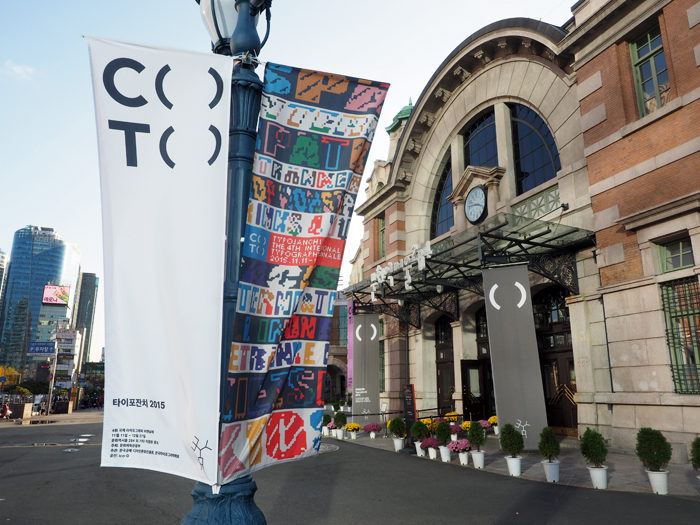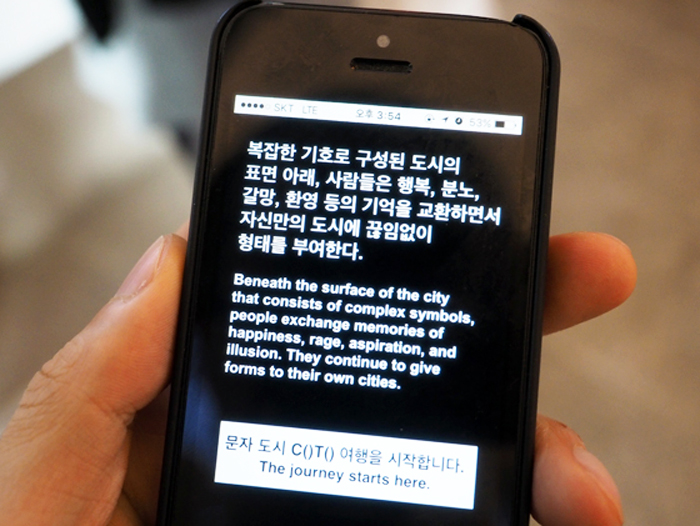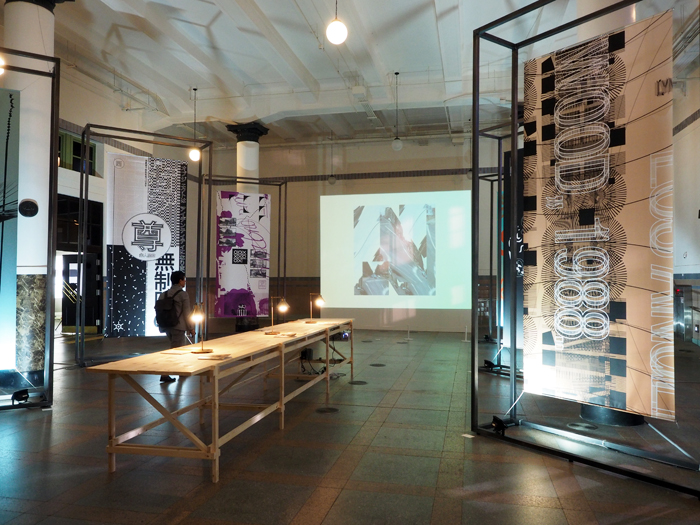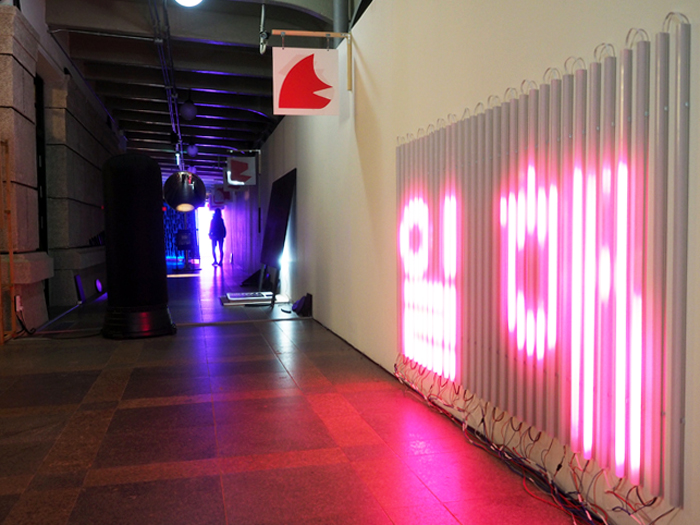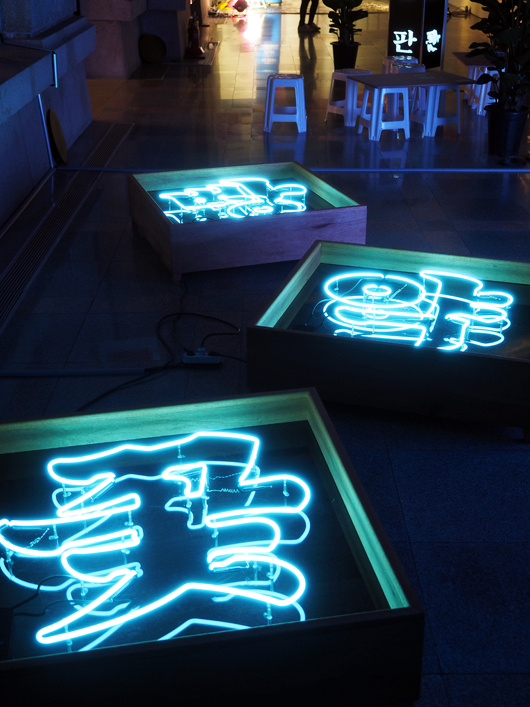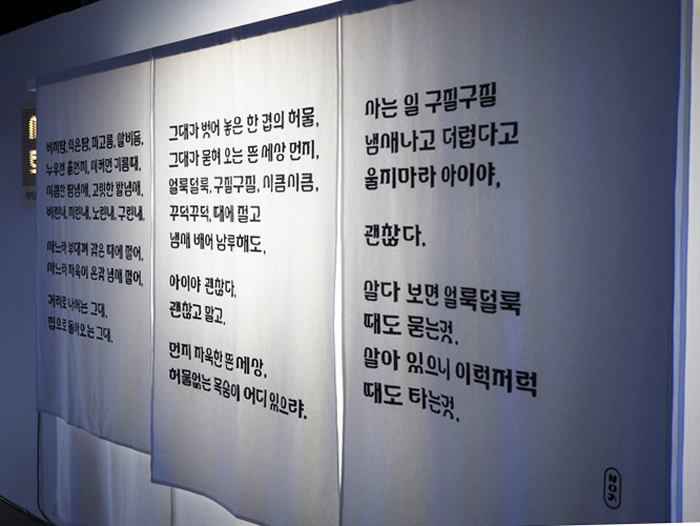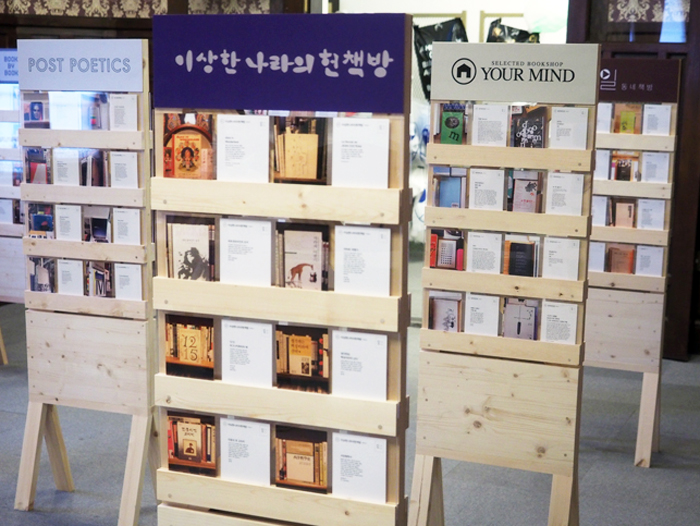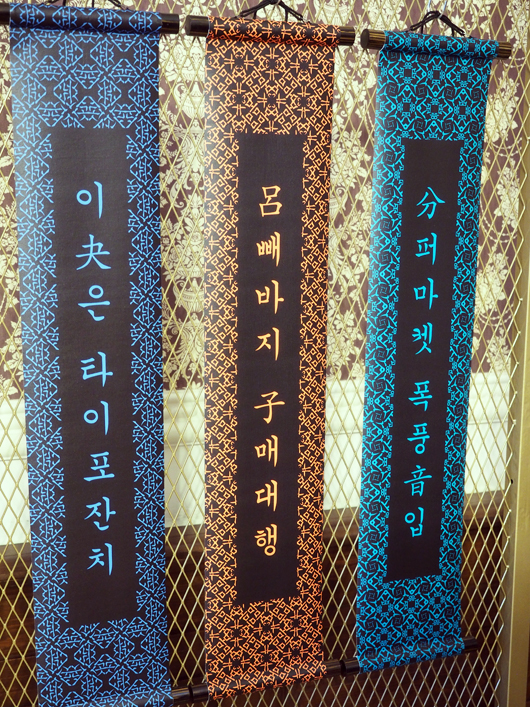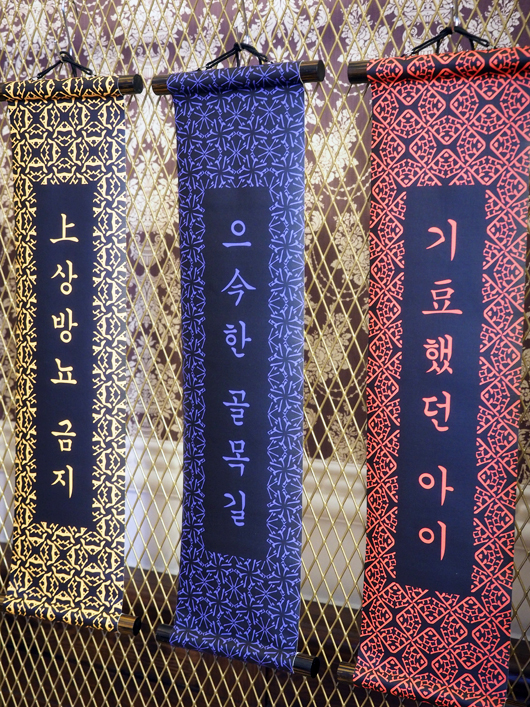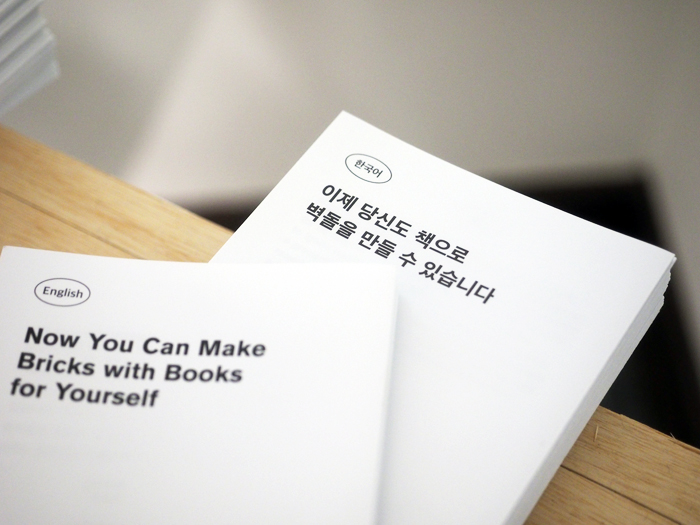
타이포잔치 2015 : 도시와 문자, 그 긴밀한 관계 속으로
올해로 4회를 맞은 ‘국제타이포그래피비엔날레(타이포잔치)’는 세계 22개국 91명의 작가가 참여해 준비한 세계 유일의 타이포그래피 비엔날레다. 이번 타이포잔치 2015의 주제는 ‘도시와 문자’다. ‘도시’라는 문명의 터전에서 문화의 가장 기본이 되는 문자가 어떻게 살아 숨쉬며 우리와 호흡하고 있는지를 다양한 작품들에서 만날 수 있다. 오는 12월 27일까지 문화역서울284에서 진행된다.
타이포잔치 2015 : 제4회 국제타이포그래피비엔날레
“일어나서부터 잠들기까지, 우리의 일상에서 문자가 없어진다면 어떻게 될까?”
매일 아침 습관적으로 쳐다보는 스마트폰 화면이 텅 비어있다면? 스마트폰 뿐만 아니라 컴퓨터에도, TV에도, 신문에도, 도로에도, 지하철에도 아무런 글자가 없다고 상상해보라. 우리의 일상은 급브레이크를 밟은 것처럼 큰 파열음을 내며 멈출 수 밖에 없을 것이다. 특히 대도시에 살고 있다면 더욱 그렇다. 이 거대하고 복잡한 도시가 아무 문제없이 자연스럽고 원활하게 유지되기 위해서는 문자라는 문명의 질서가 반드시 필요하다. 우리에게 문자는 산소와 같다. 인간의 문명과 문화에서는 문자란 언제나 존재해야 하는 것이다.
“타이포잔치가 도시를 주제로 삼은 것은, 아마도 사람의 삶이 가장 복잡하게 뒤섞인 곳이기 때문에 도시 구석구석에 스며 있는 문자들의 생태가 궁금해서였을 것이다.
‘C( )T( )’라는 타이포잔치의 로고에 포함된 ‘( )’는 다양한 해석과 참여를 의미하기도 하지만, 도시를 횡단하는 여러 단면을 끌어내어 담아내보려는 의도가 포함되어 있다.”
-민병걸, ‘결여의 도시’ 큐레이터
타이포잔치는 이런 사실을 극명하게 보여준다. 심지어 여기서 한발 더 나아가 문자와 타이포그래피를 우리 생활의 주역으로 끌어올린다. 언제나 조연에 불과하던 이들이 주인공이 되어 선사하는 풍경은 충분히 이색적인 경험이다. 이차원적인 평면에 납작하게 붙어있던 문자들이 도시의 문맥을 타고 풍성하게 부풀려져 우리의 감각 속으로 스며든다.
“텍스트가 난무하는 광고판과 거리에 흩어진 전단지들은 속도를 제한하고, 방향을 지시하는 표지판들과 치열하게 싸우고, 지하철 가판대에 있던 신문과 잡지 속 정보들은 손안의 전자기기 속으로 들어와 도시인들의 시선을 독차지하며, 다소곳이 건물 한켠에 자리잡았던 간판들은 다양한 형태와 기술로 치장하고 도시 전체를 뒤덮는다. (중략)
그로써 이 시대에 필요한 가치를 제안하며, 도시 환경 속에서 문자 문화에 관심을 가져온 디자이너와 예술가들의 시선을 여러 사람들과 공유할 수 있는 기회를 갖고자 한다.”
-김경선, 총감독